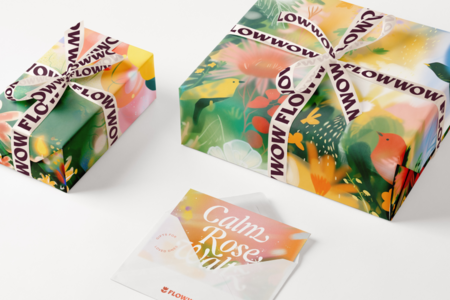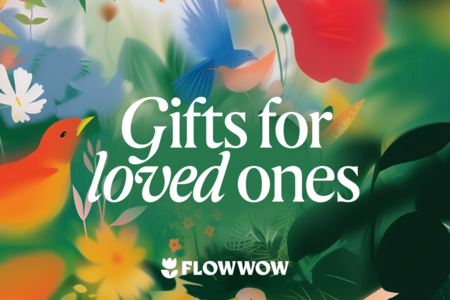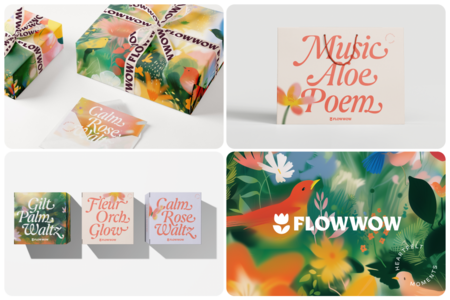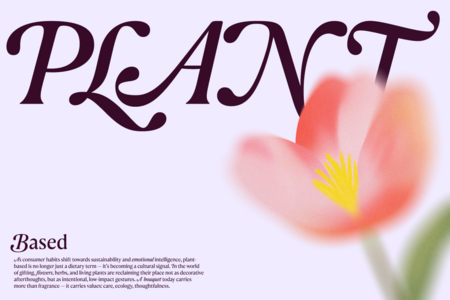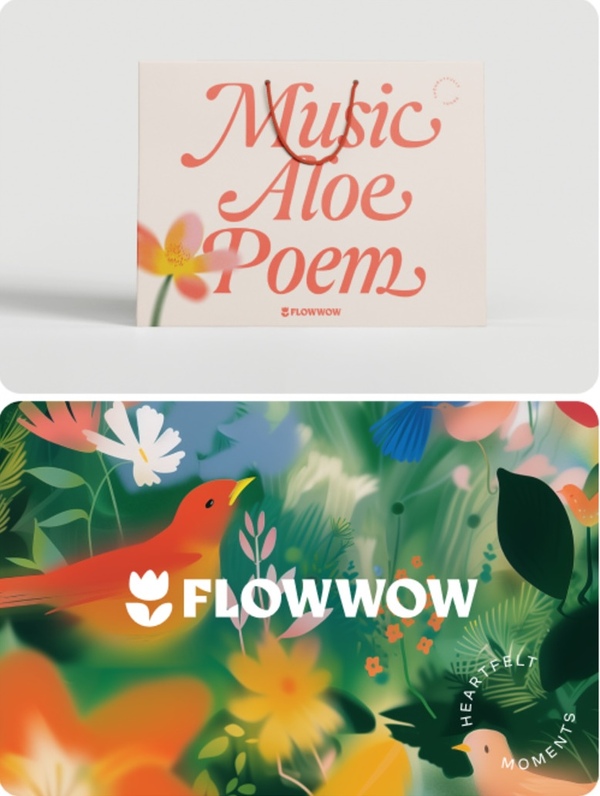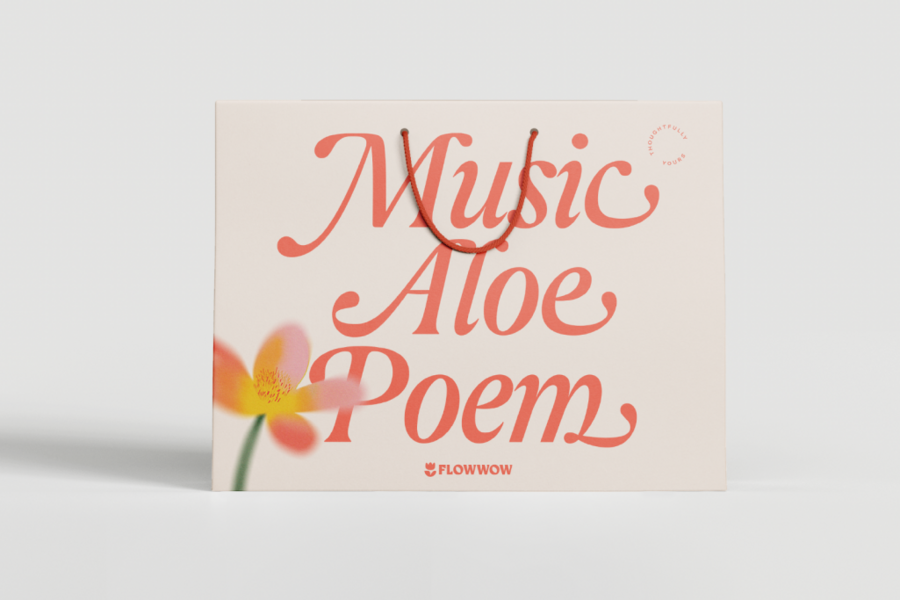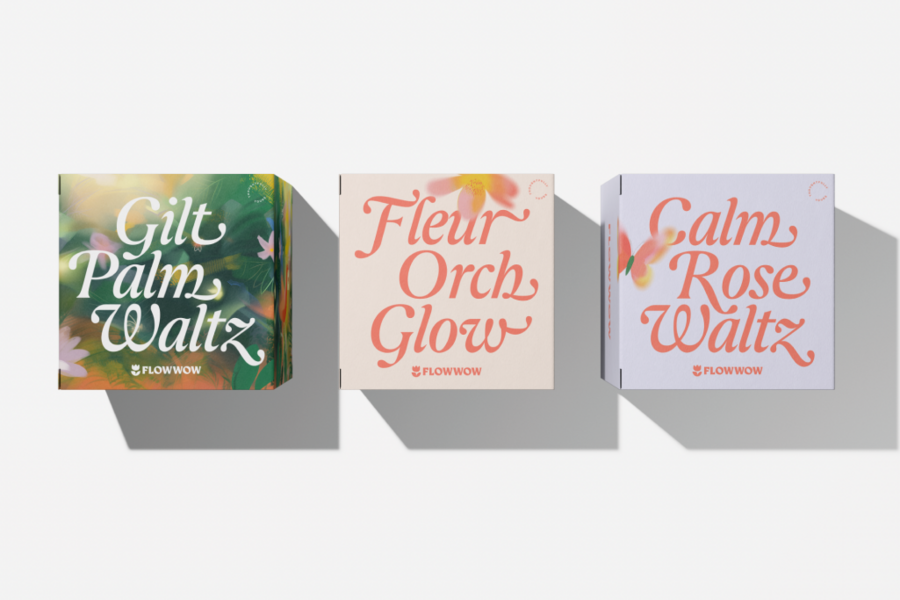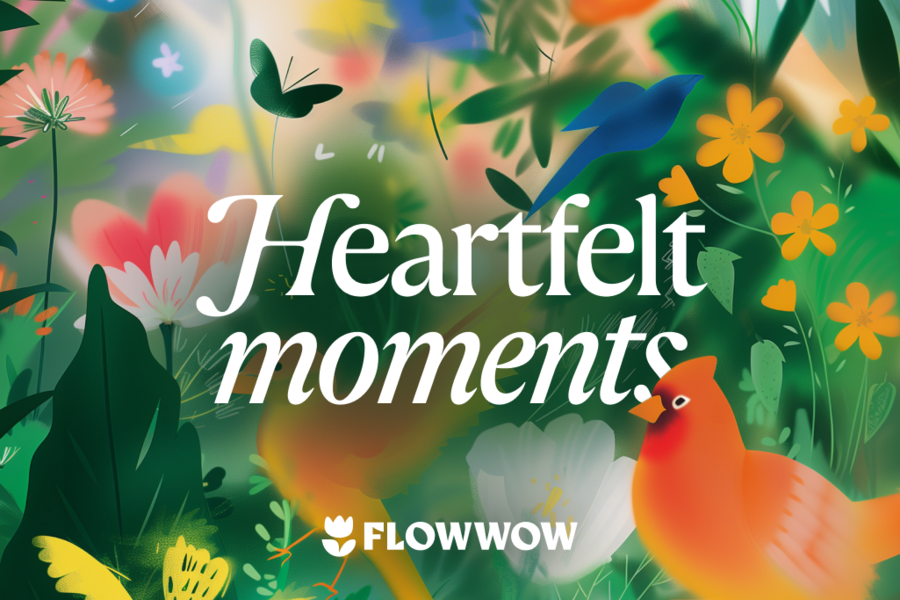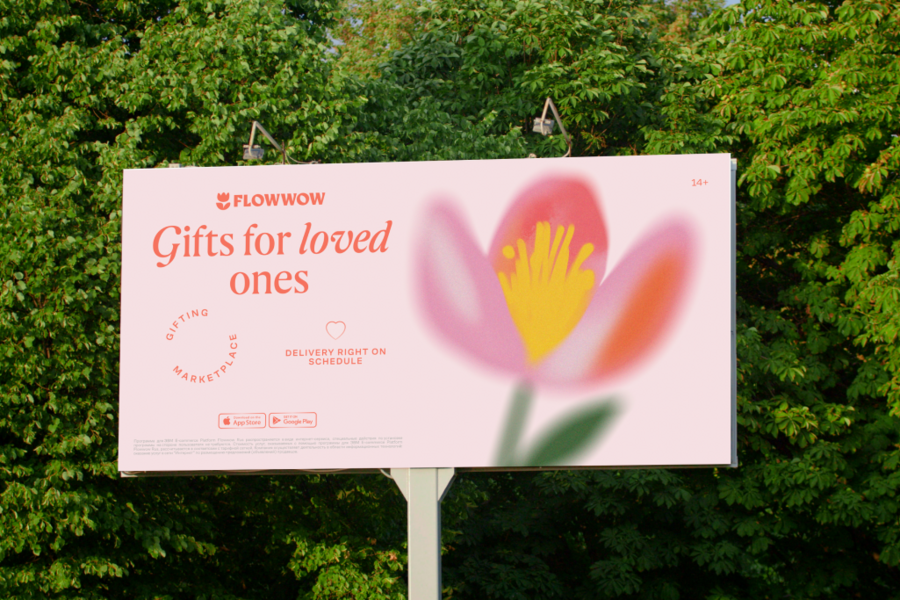
Flowfont — фирменный шрифт Flowwow, маркетплейса цветов и подарков. Это изящный акцидентный гибрид антиквы и гротеска, в котором переосмыслены особенности различных исторических стилей. В его основе — живая, ритмичная структура нидерландских шрифтов XVII века, дополненная декоративным богатством переходных антикв XVIII века.
Вместо засечек Flowfont использует мягкие окончания штрихов, отсылающие к формам растений и отражающие ботаническую тематику бренда. Такая конструкция позволяет создавать плотные, звучные текстовые блоки, вдохновлённые фактурой фотонабора. Шрифт особенно эффективен в коротких заголовках для соцсетей и наружной рекламы — это его ключевые области применения.
Отличительная особенность Flowfont — курсивные заглавные буквы с завитками, используемые непосредственно в прямом начертании. Они придают движению и акцент ключевым словам. Эта энергия продолжается в курсиве, где изящные лигатуры и плавные штрихи-завитки создают выразительный ритм.